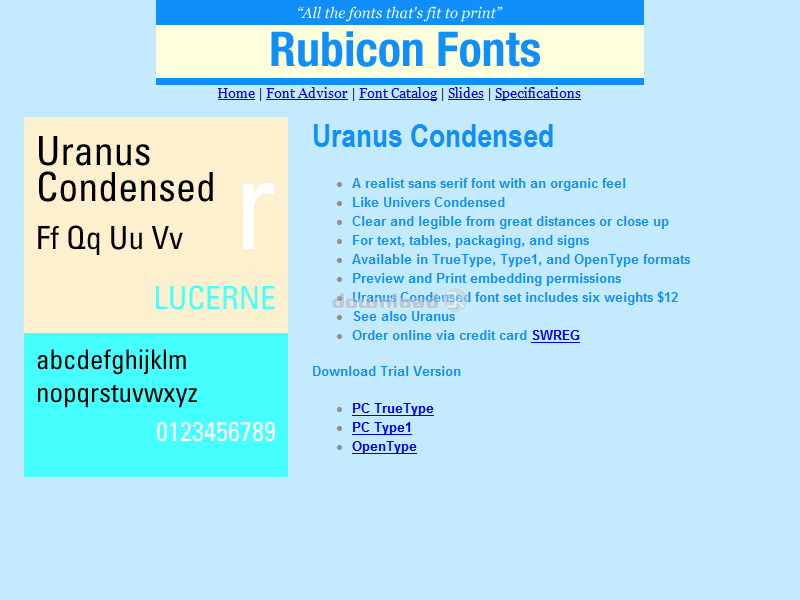
"Реалист шрифт без засечек, органический вид"
Сокращенный реалист шрифт без засечек с органическими чувствую. Как Univers Condensed. Четкий шрифт это разборчиво с больших расстояний или крупным планом. Установите более текста в ограниченном пространстве без потери четкости. Отлично подходит для таблиц, заголовков, упаковки и знаков. Использование в любой размер. Точная и намекнул, соответствующий шрифт метрик, стандартный набор символов, кернинг пар. Профессиональное качество печати на струйных, лазерных, наборщик до 3500 точек на дюйм. Покупатели получают 6 вариантов шрифта следующим образом: свет, свет Oblique, Normal, Oblique, Bold, Bold Oblique.Требования: Older versions of Windows require Adobe Type Manager.